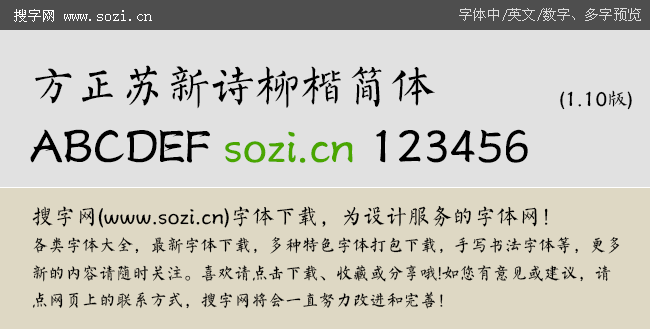
方正蘇新詩柳楷簡體
搜字網(wǎng)提供一款方正蘇新詩柳楷簡體中文字體下載,方正蘇新詩柳楷簡體是一款手寫風(fēng)格的楷體書法字體,該字體書寫端正,簡潔耐看,整體效果十分出色,適合應(yīng)用于廣告設(shè)計、名片設(shè)計、包裝印刷、產(chǎn)品設(shè)計等應(yīng)用。